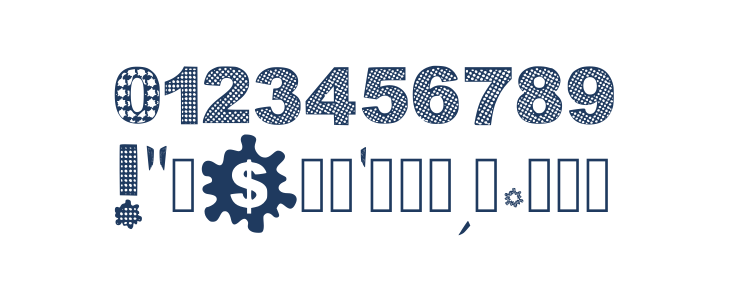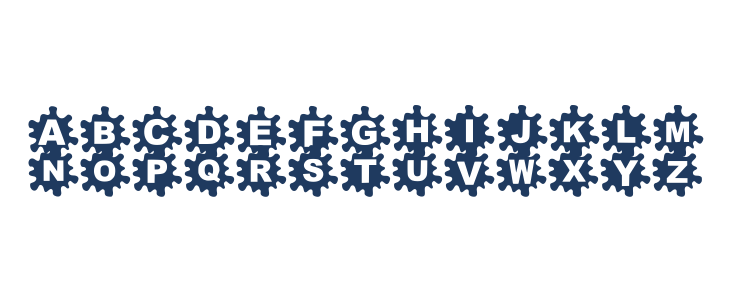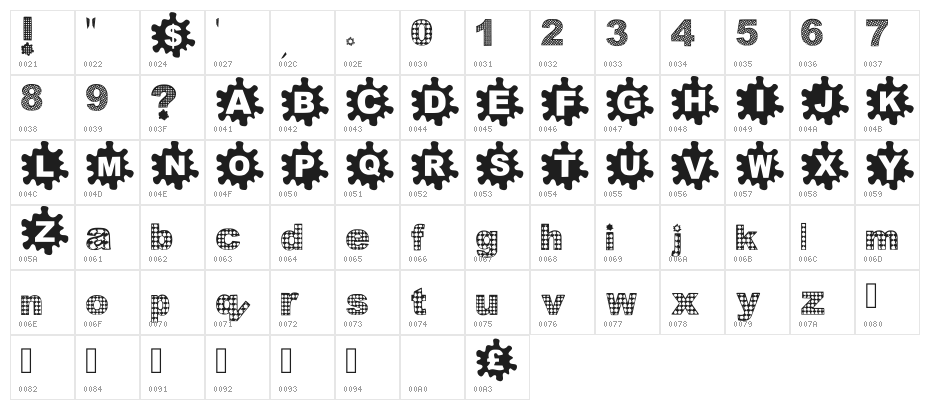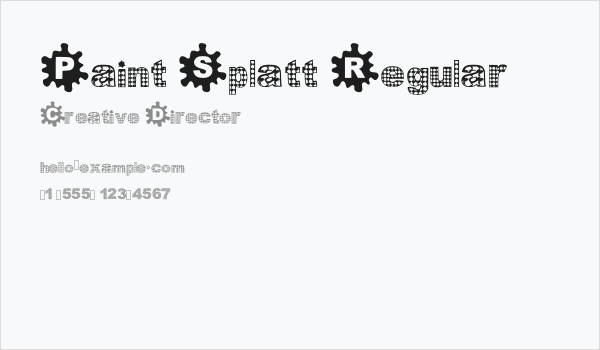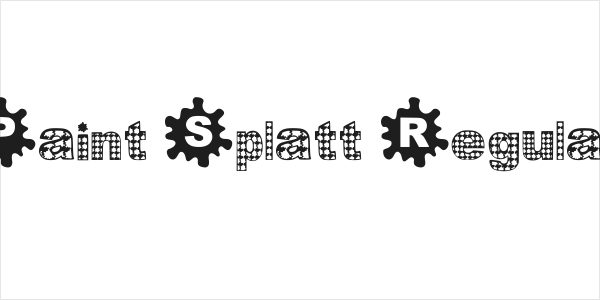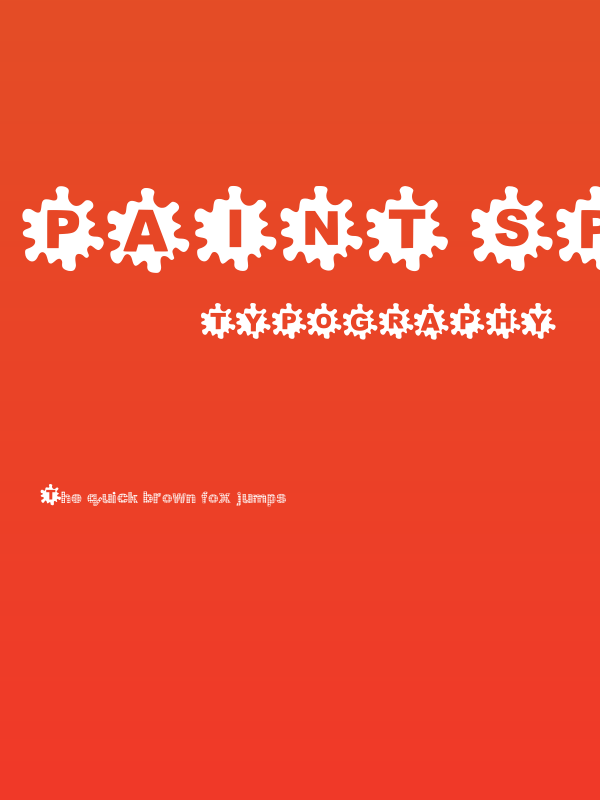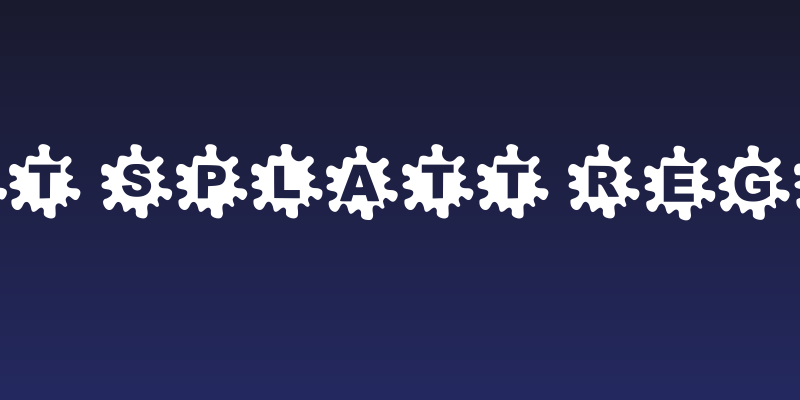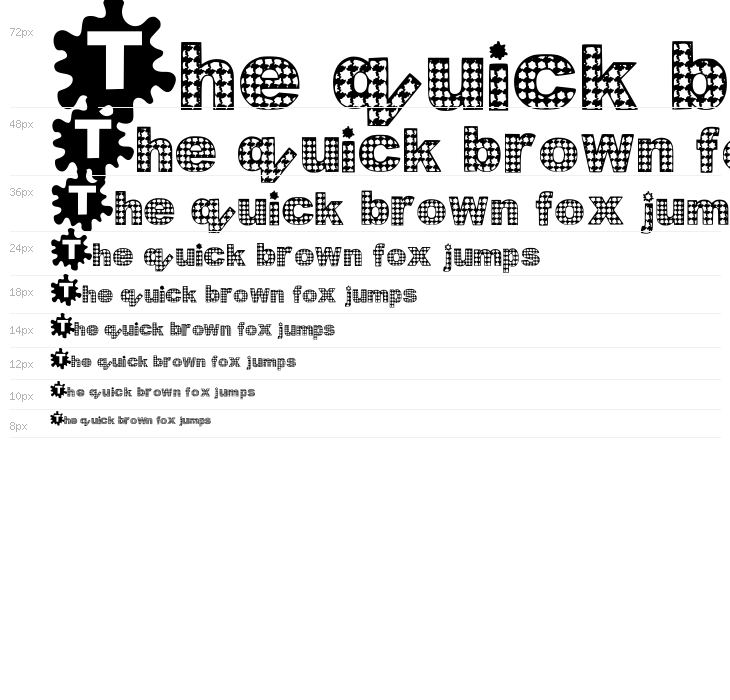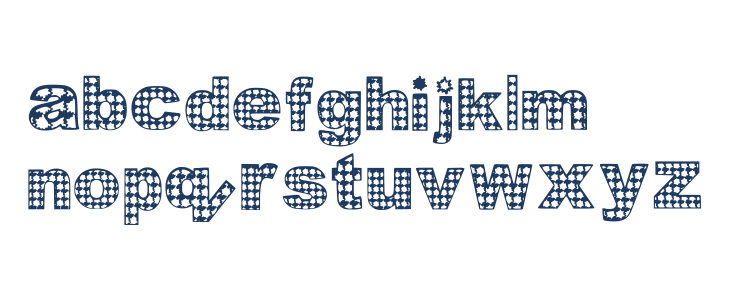
Paint Splatt Regular Font
| Stile generale | Decorative, Playful, Whimsical |
| Caso d'uso | Headlines, Posters, Logos, Event Materials |
| Progetti proposti | Children’s books, party invitations, posters, playful branding, event flyers. |